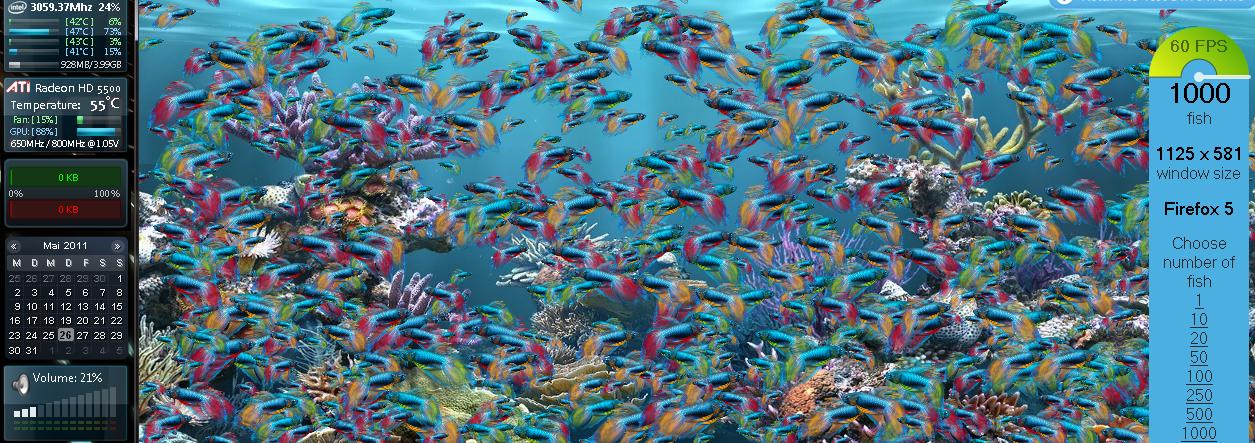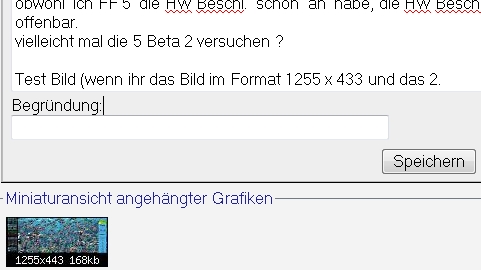
Firefox 4.0 Schriftart ändern?
ich habe mich lange gesträubt, und jetzt doch vo ndem blöden Update-Dienst "übereden" lassen, Firefox 4.0 zu installieren.
Aber irgendwie ist die Schrift viel schlechter!
Ich hätte gerne genau die gleiche Schriftart und größe wie bei Firefox 3.6....
Kennt jemand die Schriftart und Größe?
Wenn einer behauptet, die Schriftarten wären identisch, muss ich drigend zum Augenarzt.... schon wieder!
hardwarebeschleunigung ausmachen .
Jupp, hätte der TE nur 15 Sekunden an Google oder die Forensuche verschwendet hätte er das auch alleine raus bekommen.
Edit: Bringt nichts?! Sieht genau so aus!
Nochn Edit: jetzt gehts!
Gibts es Nachteile?
Natürlich gibt es den Nachteil der fehlenden Hardwarebeschleunigung. Ich kann nur jeden raten, seine Unzufriedenheit an Mozilla zu melden.
Man sollte seine Unzufriedenheit lieber bei Microsoft melden, denn die sind dafür verantwortlich. Das Problem besteht nämlich durch die Clear Type Methode von Microsoft und betrifft alle Browser die Hardwarebeschleunigung verwenden!
Das ist etwas zu einfach dargestellt. Chrome verwendet auch Hardwarerendering ohne diese für die Schriften zu verwenden. ist ein guter Kompromiss, wie ich finde. MS hat auch die Möglichkeit vorgesehen, das Rendering entsprechend zu konfigurieren. Das Addon Anti-Aliasing Tuner für Firefox 4 macht nichts anderes, als diese Funktionen zu nutzen. Mozilla sollte diese Optionen direkt im Browser zur Verfügung stellen. Peinlich ist allerdings, dass es MS ebenfalls versäumt hat dies im IE9 bereitzustellen. Den Artikel in der c't zum Thema fand ich sehr gut.
Ja, ich habe das recht einfach dargestellt. Natürlich gibt es Möglichkeiten diese unangenehmen Effekte zu minimieren, oder wie im Chrome ganz zu vermeiden. Will man aber den Schriftaufbau auch beschleunigen, wie im FF, IE etc. wird man auf diese Probleme stoßen, sofern man Direct2D verwendet.
Zum Anti-Aliasing-Tuner: Ich habe den schon getestet und bekomme da leider, egal mit welchen Einstellungen, kein vollständig ordentliche Darstellung mit hin. Es wird dann in einigen Fällen zwar die Schrift besser gerendert, aber es entstehen dann z.B. bei hover Effekten negative Auswirkungen.
So oder so ist das alles noch recht unkomfortabel gelöst. Man wird sehen wie sich das in Zukunft entwickelt. Allgemein kann man aber sagen, wem die Schrift Darstellung absolut nicht zusagt, sollte die Hardwarebeschleunigung einfach deaktivieren.
Wenn man mit aktiviertem Direct2D Fontrendering die Schrift stark vergrößert, kann man erkennen, welches Potential in der Methode steckt. Bei Displays mit hoher Pro Zoll Auflösung, so ab 300 ppi, sieht das bestimmt super aus. Bei den gängigen Auflösungen und Größen am PC zwischen 90 un 110 ppi ist auch meiner Meinung nach keine ordentliche Darstellung sowohl im Firefox 4, als auch im IE9 möglich, weswegen ich die HW Beschleunigung im Firefox auch abgeschaltet habe. Eine Möglichkeit Mozillas wäre es, ähnlich wie Chrome die Schrift in Software zu rendern, so kann man die HW Beschleunigung für aufwendige Grafikdarstellung aktiviert lassen. Solange die meisten Webseiten ohne HW Beschleunigung keine Performanceprobleme machen, hat mein ja keine großen Nachteile, wenn dies aber in zukünftig notwendig wird, wäre eine entsprechende Option praktisch.
ich wollt mich da nicht mehr groß rein melden
aba wenn ich so was lesen ?
Verstehe ich nicht bei mir ist die Schrift Top in Ordnung allerdings nun Firefox 5
Beta 2 nur im IE 9 hatte ich so ein Problem .
hatte mit dem 4 keine Probleme aba diesen nur sehr kurz am laufen vielleicht ist die 5 Beta besser was das mit der Schrift an geht?
Die HW Beschl. ist an und funktioniert
habe ich mehrfach getestet GBU wird gut ausgelastet
die Schrift wurde selten und nur bei sehr wenigen Seiten schlecht dargestellt auch wenn HW aus war .
weg bekommt habe ich das, einfach bei Fonts beim FF einfach die Font Gestaltung der Web. Seiten nicht überlassen das nur abschalten ,
jedenfalls bei meiner 5 Beta 2 kann ich so sagen das alle Seiten gut dargestellt
werden, also so wie man es gewohnt war und ist ( gestochen Schrift ),
obwohl ich FF 5 die HW Beschl. schön an habe, die HW Beschl funktioniert also
offenbar.
vielleicht mal die 5 Beta 2 versuchen ?
Test Bild (wenn ihr das Bild im Format 1255 x 433 und das 2. 481 x 270 pixel
wird leider auseinander gezogen hier, so zieht bei mit die Schrift aus im 5 Beta 2.